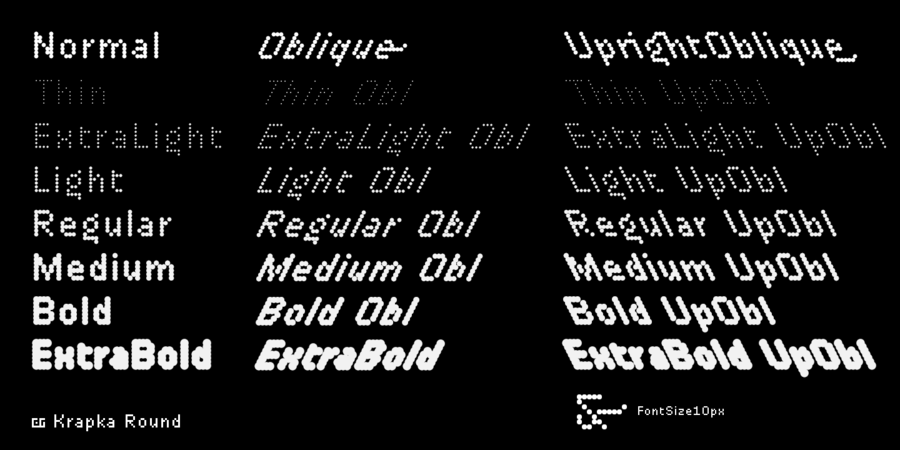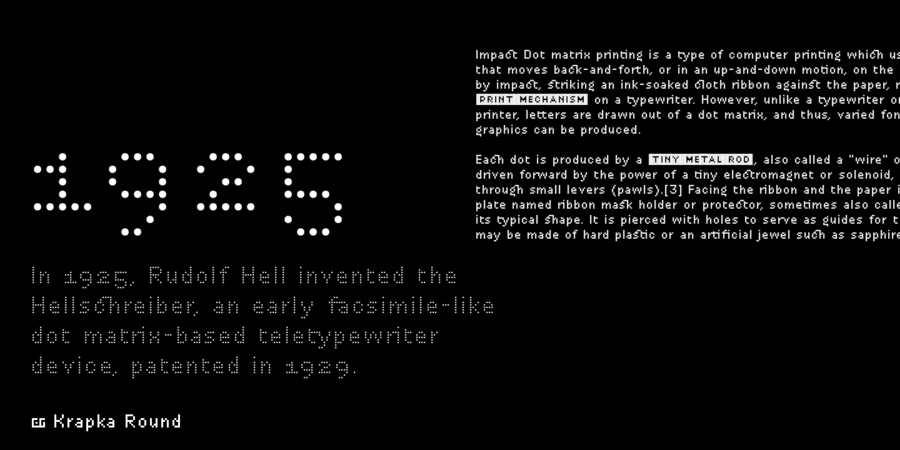
DR Krapka Round (22 шрифта)
У цьому шрифтовому сімействі піксель має круглу форму. Шрифт підтримує функції OpenType і містить капітель, лігатури, мінускульним цифри, дроби й індекси, історичні форми, стилістичні набори та розчерки. Також присутні символи, стрілки, і навіть емодзі. Для невеликих текстів рекомендується використовувати DR Krapka Round FontSize10px з розміром шрифту рівно 10 пікселів. Сімейство шрифтів DR Krapka Round підтримує європейські мови на основі латинки, кирилицю, в тому числі азіатську, і грецьку абетку. Якщо ви хочете використовувати шрифти з іншою формою пікселів, є й інші сімейства DR Krapka: DR Krapka Square (квадрати), DR Krapka Rhombus (ромби). Шрифт розробив Дмитро Растворцев у 2020 році.
Асоціації з сімейством шрифтів DR Krapka RoundОсобистість і характер гарнітури:
тонкий, легкий, автоматичний, комп'ютерний, електронний, машинний, матричний, інженерний, точний, прозорий, невагомий, байдужий, гладенький, пластмасовий, помітний, яскравий, М'який, значний, впевнений, важкий, дивний, експериментальний, грайливий, робочий, рівний, логічний, холодний, техногенний, твердий, стійкий, прямокутний, міський, урбаністичний, індустріальний, мужній, армійський, промисловий, незграбний, активний, суворий, брутальний, ігровий, тісний, чорний, потужний, психоделічний, швидкий, строковий, стрімкий, сміливий, рішучий
електроніка, автоматика, код, програмування, інженер, комп'ютер, IT, айтішник, айті, технології, андроїд, фантастика, дискотека, аквадискотека, гра, наука, рентген, математика, хакер, комп'ютерна гра, цегла, іграшка, мультфільм, дитяча книжка, анімація, екскаватор, урбаністика, авто, інструмент, промисловість, армія, завод, верстат, тара, склад, ремонт, депо, уніформа, вагон, автомат, шутер, екшен, страйкбол, будівництво, будматеріали, бойовик, сталевар, робочий, кубики, графіка, ілюстрація Гарнітура має ознаки стилів: